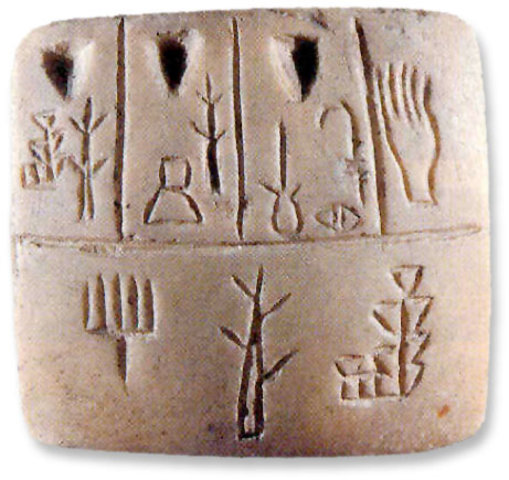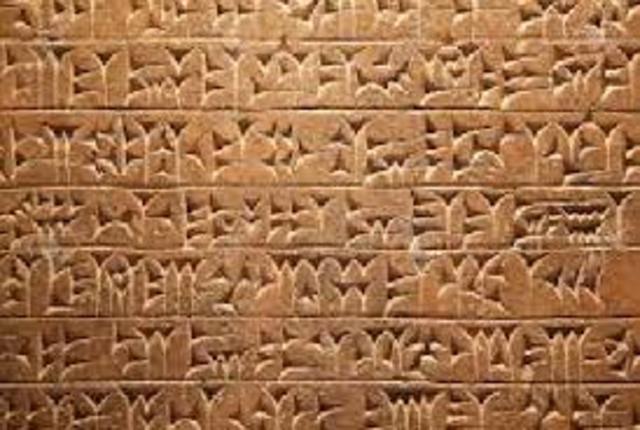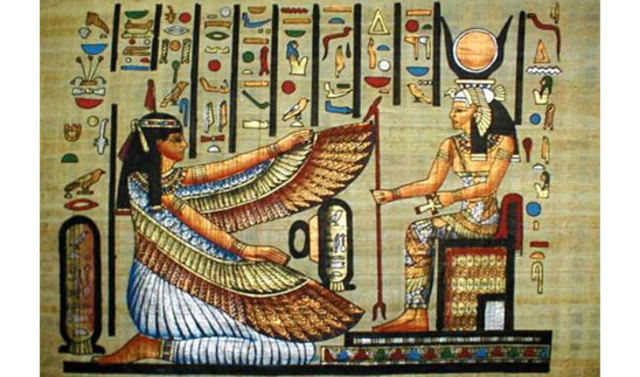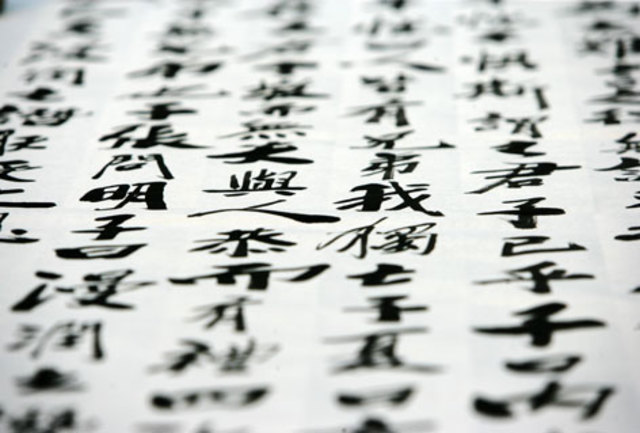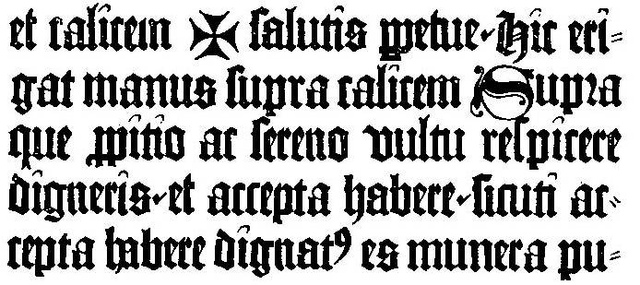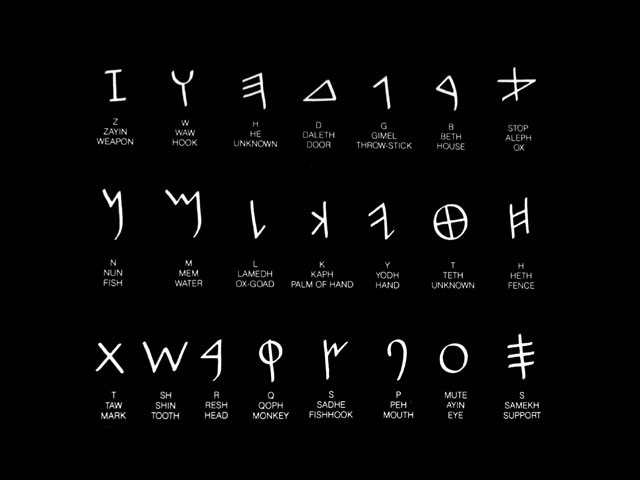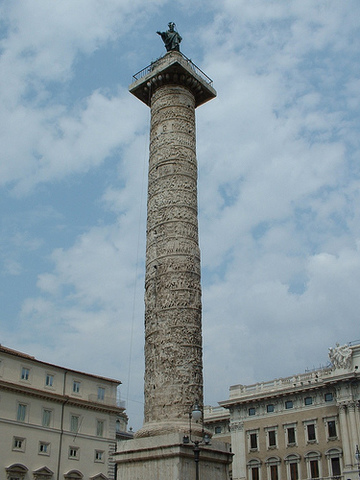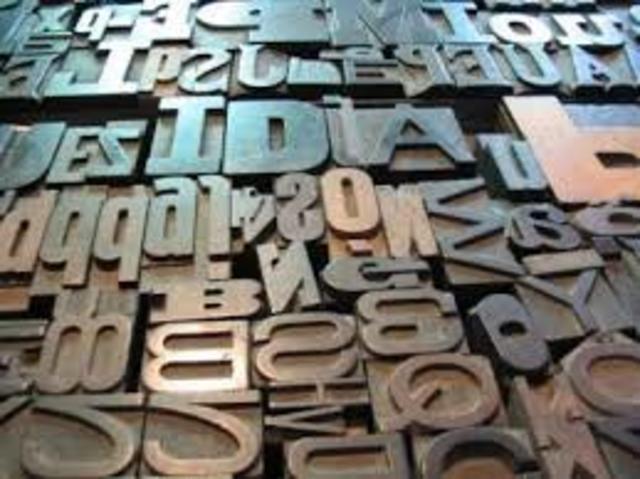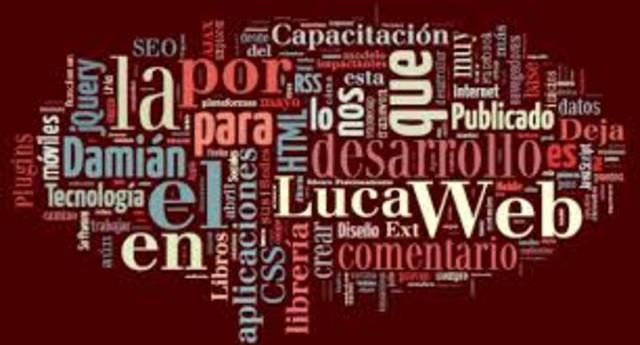
basa su sistema en el dibujo de formas, seres u objetos, que situados uno detrás de otros explican una historía,un hecho, un acuerdo. La escritura pictográfica supone, pues, un cuento sin palabras, en el que no interviene el sonido de las palabras
u origen es el alfabeto latino, con el que en la Edad Media escribían los monjes copistas sobre pergamino. Aproximadamente en la misma época la cultura islámica desarrolla su propia caligrafía, basada en el alfabeto árabe, y debido a la prohibición religiosa de representar seres vivos, la convierte en un arte decorativo de amplio uso en la arquitectura.
es empleaba una caña biselada con la que se imprimían "cuñas" en la arcilla; al principio, cercadas por cartuchos; luego alineadas y sin cartucho, de izquierda a derecha. El sistema (que duró hasta el siglo I) era muy complejo.
Fue utilizado desde la época predinástica hasta el siglo IV. Los antiguos egipcios usaron tres tipos básicos de escritura: jeroglífica, hierática y demótica; esta última corresponde al Periodo tardío de Egipto.
Es comúnmente aceptada como una de las formas más antiguas de expresión escrita, según el registro de restos arqueológicos.
Los sumerios comenzaron a escribir su idioma mediante pictogramas, que representaban palabras y objetos, pero no conceptos abstractos. -
La caligrafía china es 100% visual (diseños abstractos), no es alfabético. El descubrimiento de la imprenta por parte de los chinos tiene 2 etapas:
1) Siglo III AC:Se utilizaban sellos de arcilla, tallados en Jade, Plata, Oro y Marfil.
En el año 165 DC se comienza a implementar las inscripciones en piedra con relieve entintado.
2) Siglo III DC:Aparecen los sellos positivos y negativos.
En el año 770 DC acontece la impresión más antigua, el grabado en madera (Xilografía). -
Basándose en la escritura cuneiforme de los sumerios y en los jeroglíficos egipcios, crearon un alfabeto de 22 consonantes, con significación hebrea, que datan del año 1000 a. C. y que se conocieron cuando un campesino encontró vasos de bronce, en 1876, con inscripciones fenicias, y los rompió para venderlos creyendo que eran de oro. Este alfabeto fue la base del alfabeto griego que lo perfeccionó, añadiéndole las vocales.
En el Imperio Romano con el levantamiento de la columna en honor al emperador Trojano, en la base se grabó sobre una superficie dura un tipo de tipografía a partir de ahí, se pueden destacar sus caracteristicas tales como la presencia de serif para compensar los rasgos verticales y ligeramente gruesos. En esta partícular tipografía no hay minusculas y estas son representadas de igual manera que las mayusculas epro de un tamaño menor que estas.
Es la caligrafía mas antigua de Roma que dio origen a mayúsculas actuales. Se caracterizan por su forma de líneas rectas y pequeñas serifas en las terminaciones. Sus curvas son particularmente circulares con trazos gruesos y estrechos. Suelen tener la misma altura y anchura.
A partir de los siglos VIII se comienza a utilizar la escritura carolina en Europa específicamente en el imperio carolino al cual le debe su nombre en la Edad Media se originaron formas particulares de escritura esto, pero la predominante por sus características y expansión por Europa fue la Escritura carolina.
Los primeros tipos móviles, inventados por Johann Gutenberg, y el tipo de letra redonda o romana que le siguió en Italia, imitaban el estilo manuscrito de esos países en boga en aquellos momentos.
La imprenta en Europa se desarrolló en el auge del Renacimiento; sin embargo, los primeros impresos de Johannes Gutenberg como la Biblia de 42 líneas utilizaron un estilo de letra del período gótico la cual se le denominó: textura. -
Ya los romanos tuvieron sellos que imprimían hojas de inscripciones sobre objetos de arcilla alrededor del año 440 a. C. y el 430 a. C. Entre 1041 y 1048, Bi Sheng inventó en China. En 1234 artesanos durante la dinastía Koryo (en la actual Corea), conocedores de los avances chinos con los tipos móviles, crearon un juego de tipos móviles de metal que se anticipó a la imprenta moderna, pero lo usaron raramente.
A comienzos del siglo XX, la búsqueda de formas tipográficas y modos de hacer más adaptados a las necesidades contemporáneas se sintió como una auténtica necesidad impulsada por el deseo de reflejar el espíritu de una época en rápida y continua transformación.